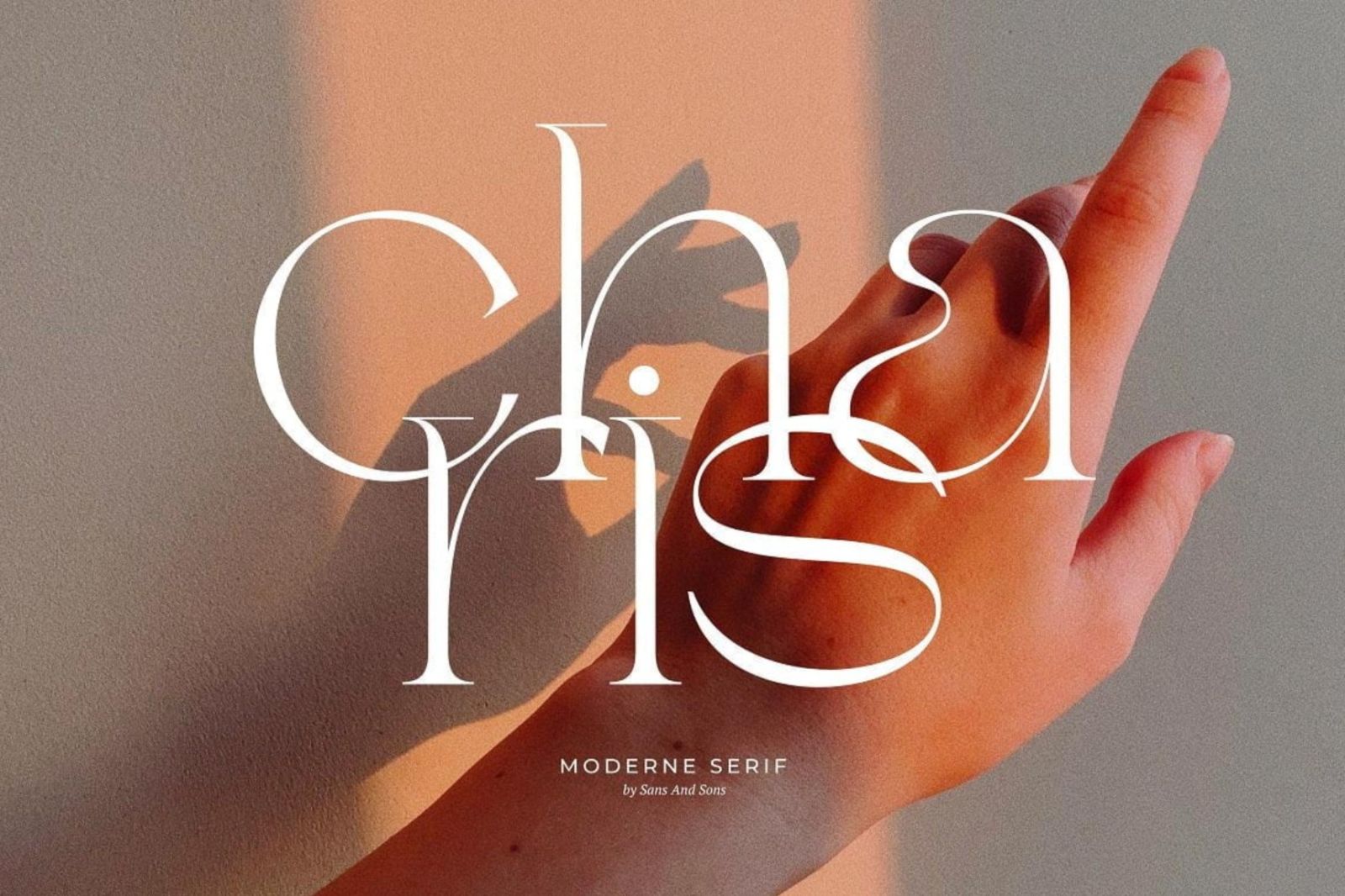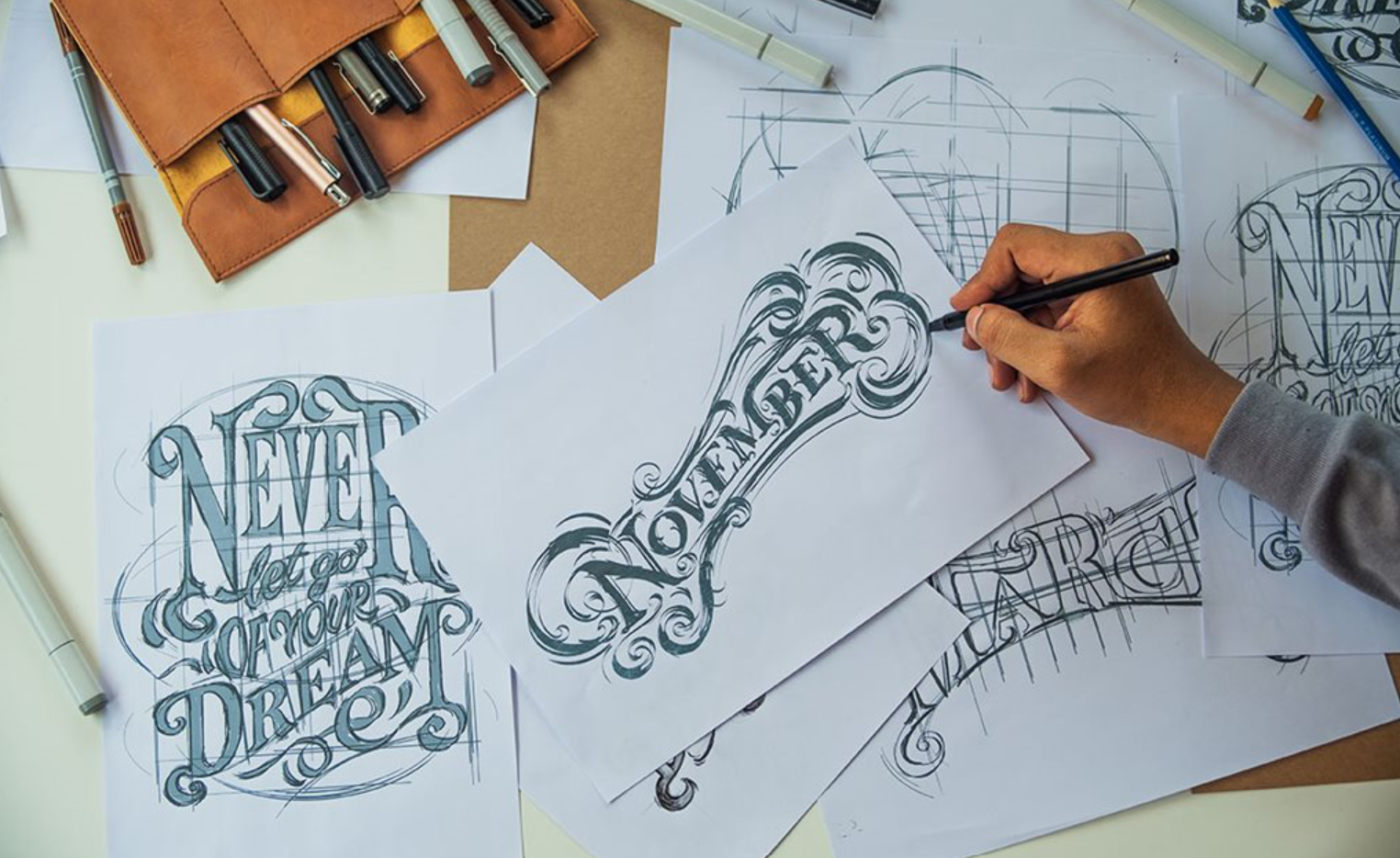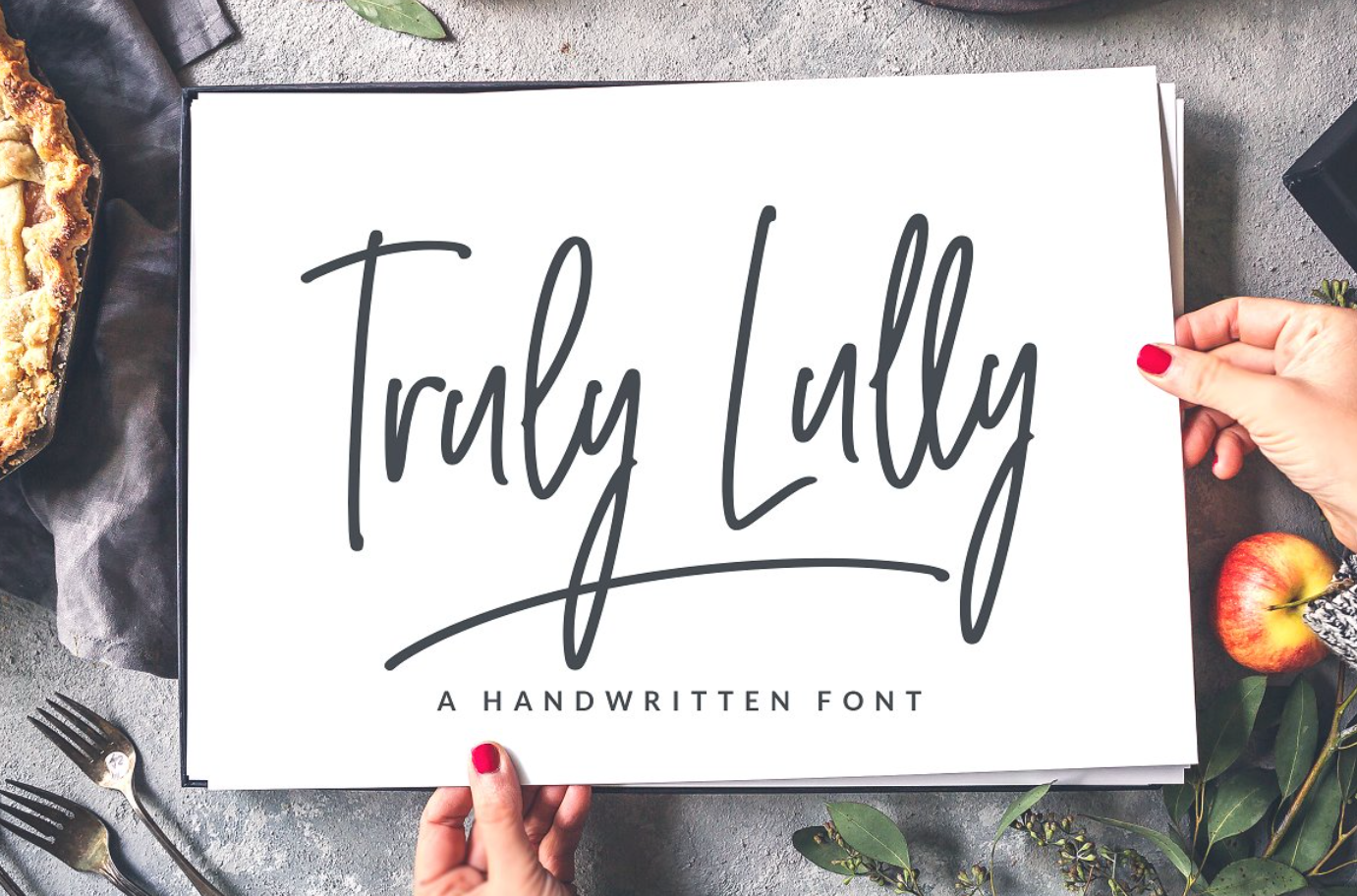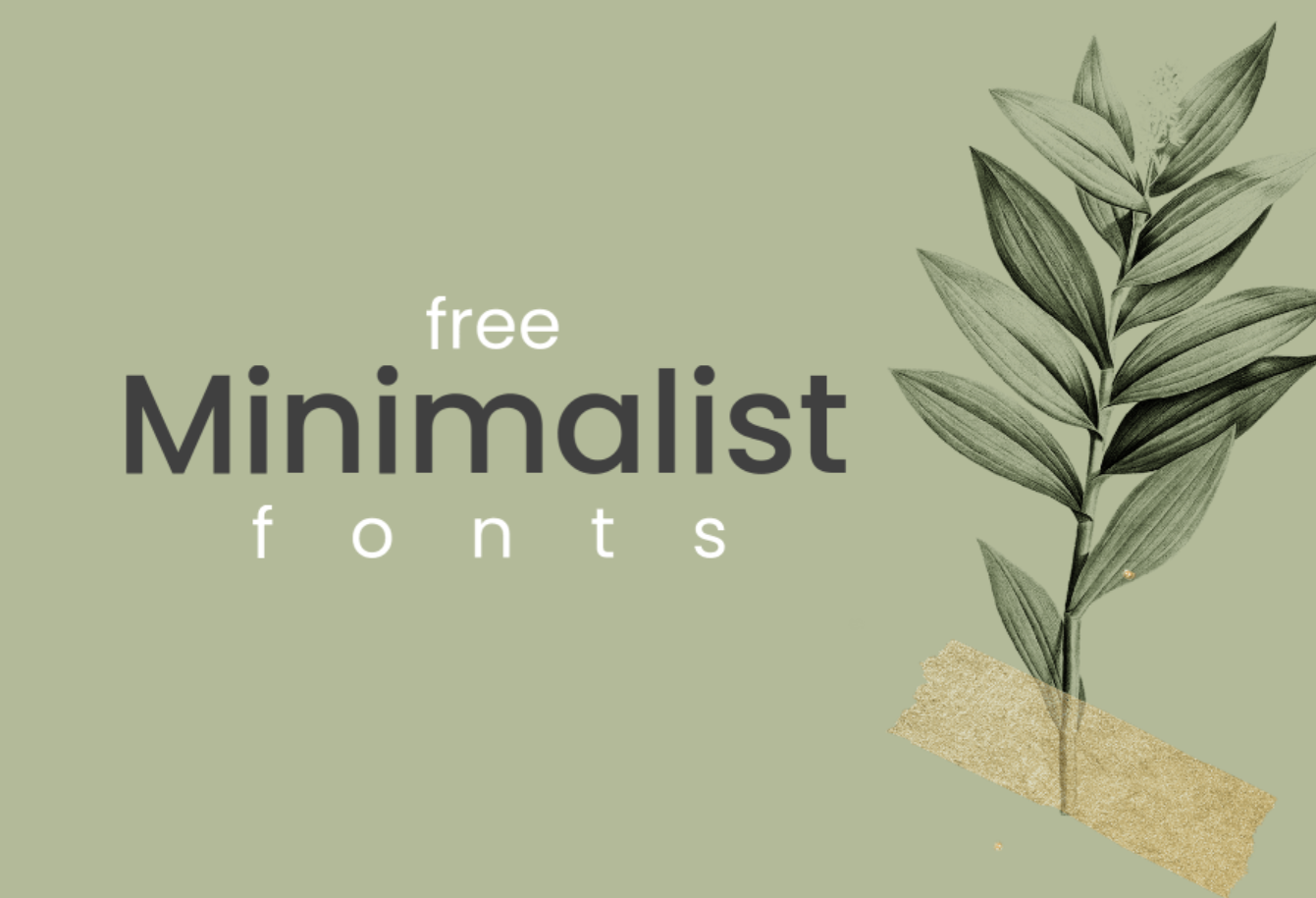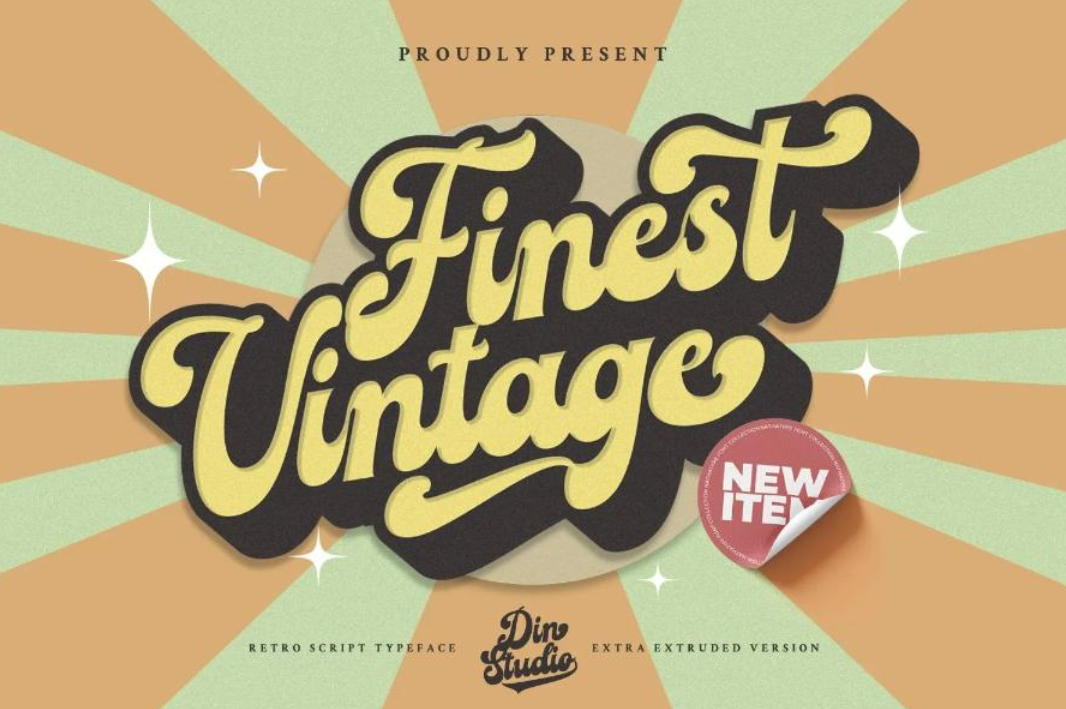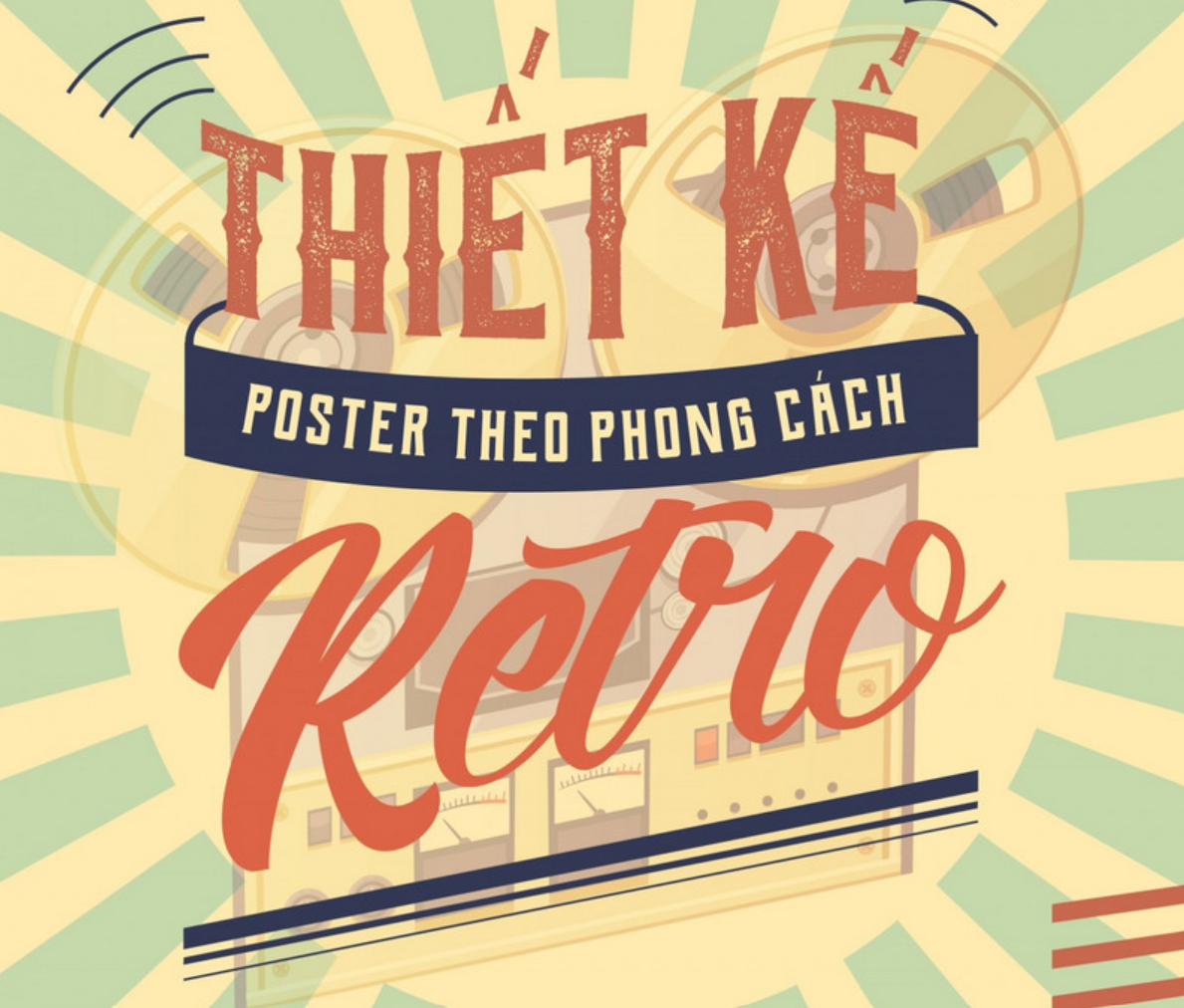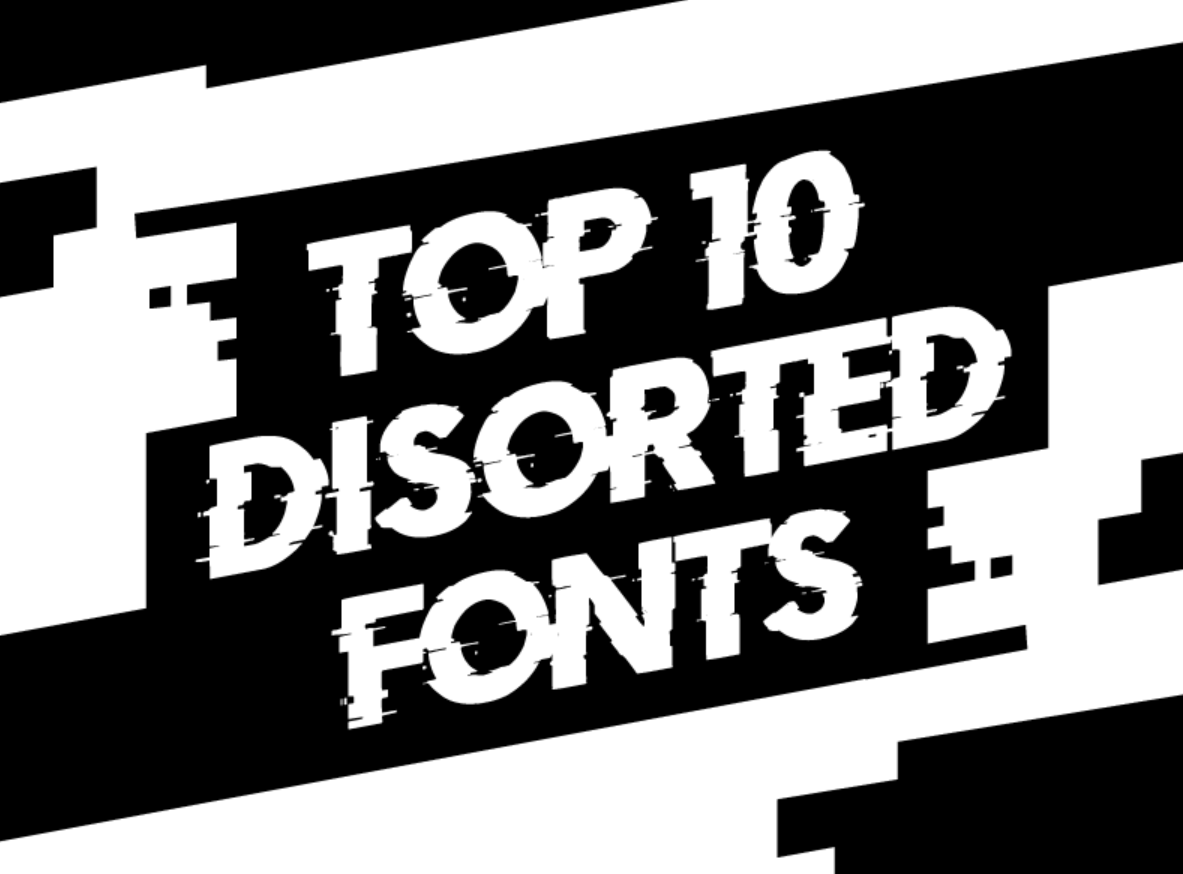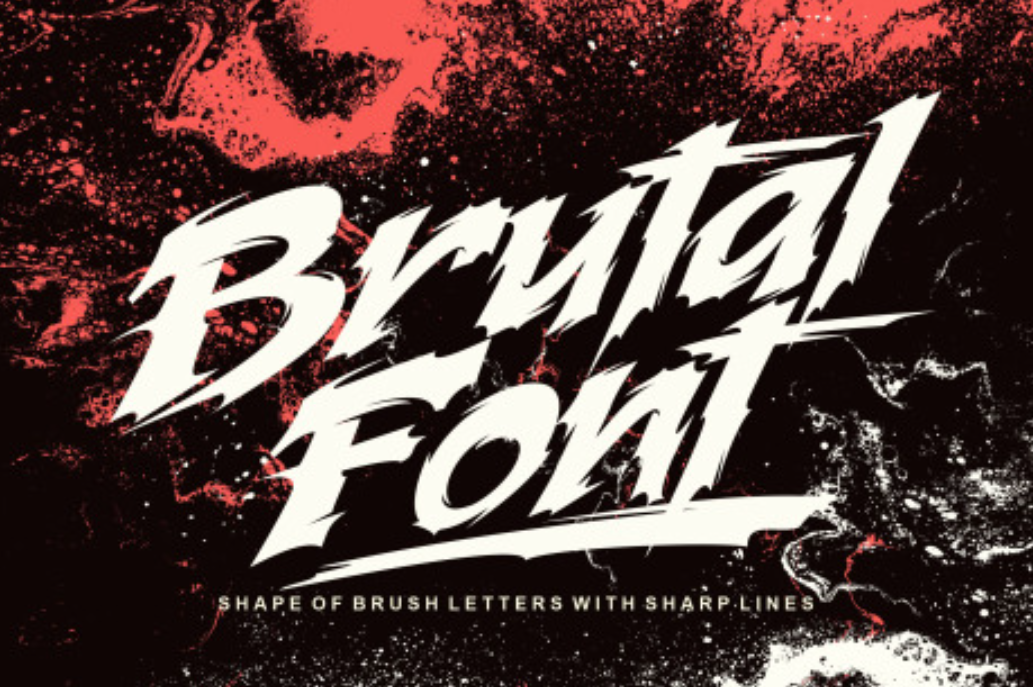
Đột Phá Cùng 6 Xu Hướng Font Chữ Đẹp Tạo Nên Sự Khác Biệt Trong Mỗi Thiết Kế Của Bạn
Bài viết giới thiệu sáu xu hướng typography đột phá, mở ra những hướng đi mới cho thiết kế hiện đại. Bạn sẽ được cập nhật những phong cách chữ sáng tạo cùng với phân tích chi tiết về cách ứng dụng chúng để nâng tầm dự án thiết kế của mình.
Trong thế giới thiết kế, font chữ không chỉ đơn thuần là công cụ để truyền tải thông điệp mà còn là yếu tố quyết định giúp tạo nên phong cách, cá tính và nhận diện thương hiệu. Một thiết kế hoàn hảo luôn biết cách kết hợp màu sắc, hình ảnh và đặc biệt là typography – nghệ thuật sắp xếp chữ để kể câu chuyện của mình một cách sống động nhất. Trong bài viết này, SaDesign sẽ chia sẻ với bạn 6 xu hướng font chữ đẹp đang được dự đoán sẽ “bùng nổ” trong thời gian tới. Hãy cùng khám phá những xu hướng này, tìm hiểu nguồn cảm hứng cũng như cách ứng dụng sao cho hiệu quả nhất trong công việc thiết kế của bạn.
1. Tầm Quan Trọng của Font Chữ Trong Thiết Kế
Trước khi đi sâu vào chi tiết các xu hướng, hãy cùng nhau tìm hiểu tại sao font chữ lại đóng vai trò quan trọng đến vậy trong thiết kế. Mỗi con chữ không chỉ đơn thuần là những ký tự, mà còn ẩn chứa trong đó tâm hồn và cá tính của thương hiệu. Một font chữ được lựa chọn kỹ càng có thể:
Tạo dấu ấn riêng: Font chữ giúp thương hiệu của bạn trở nên dễ nhận diện hơn, tạo nên ấn tượng sâu sắc ngay từ cái nhìn đầu tiên.
Kể câu chuyện thương hiệu: Qua phong cách, nét chữ có thể truyền tải câu chuyện, giá trị cốt lõi và cảm xúc mà thương hiệu muốn gửi gắm.
Tối ưu hóa trải nghiệm người dùng: Trong thiết kế web hay ứng dụng, font chữ không chỉ cần đẹp mà còn phải dễ đọc, tạo cảm giác thoải mái cho người dùng.
Qua đó, việc theo dõi và áp dụng các xu hướng font chữ mới không chỉ giúp bạn bắt kịp thời đại mà còn nâng tầm giá trị thiết kế, tạo nên sự khác biệt nổi bật trên thị trường. Hãy cùng SaDesign đi sâu vào từng xu hướng cụ thể dưới đây.
2. 6 Xu Hướng Font Chữ Húa Hẹn Sẽ Bùng Nổ Trong Thời Gian Tới
2.1: Font Chữ Serif Cổ Điển Nhưng Hiện Đại (Modern Classic Serif)
Font chữ Serif từ lâu đã được biết đến với nét thanh lịch, cổ điển và truyền thống. Tuy nhiên, xu hướng hiện nay không dừng lại ở sự cũ kỹ mà đang hướng đến việc cách điệu, làm mới nét chữ truyền thống để trở nên hiện đại hơn. Xu hướng Modern Classic Serif kết hợp giữa sự sang trọng của những nét cũ và phong cách tối giản, hiện đại của thiết kế ngày nay.
Vì Sao Xu Hướng Này Nổi Bật?
Sự kết hợp độc đáo: Việc pha trộn giữa nét cổ điển và phong cách hiện đại tạo nên một sự hòa quyện độc đáo, giúp chữ viết trở nên nổi bật mà vẫn giữ được nét trang nhã.
Tạo cảm giác tin cậy: Font chữ Serif truyền thống thường gợi lên cảm giác ổn định, uy tín. Khi được cách điệu hiện đại, nó vừa mang lại cảm giác cổ điển vừa hiện đại, rất phù hợp với các thương hiệu cao cấp.
Ứng dụng linh hoạt: Xu hướng này không chỉ phù hợp với thiết kế in ấn, tạp chí mà còn được ứng dụng mạnh mẽ trong thiết kế website, blog hay branding.
Sau khi khám phá xu hướng hiện đại trong nét chữ cổ điển, chúng ta hãy chuyển sang một xu hướng mang đậm dấu ấn cá nhân và nghệ thuật font chữ viết tay. Đây là phong cách đem lại sự ấm áp và tự nhiên, giúp thiết kế của bạn trở nên độc đáo và gần gũi hơn với người dùng.
2.2: Font Chữ Handwritten (Viết Tay, Vẽ Tay Đầy Nghệ Thuật)
Trong thời đại số hóa, nơi mà máy móc và công nghệ luôn thống trị, phong cách Handwritten lại đem đến một làn gió mới – sự tự nhiên, cá tính và gần gũi. Font chữ viết tay không chỉ phản ánh cái tôi riêng của từng nghệ sĩ mà còn tạo nên một không gian “thân mật”, như đang trò chuyện cùng bạn qua từng nét chữ.
Vì Sao Xu Hướng Này Nổi Bật?
Mang đậm chất cá nhân: Font chữ viết tay thể hiện sự độc đáo và cá tính riêng biệt của từng tác giả, từ đó tạo nên dấu ấn riêng cho thương hiệu.
Tạo cảm giác ấm áp, thân thiện: Không khí “viết tay” luôn gợi nhắc đến sự gần gũi, mộc mạc, rất thích hợp cho những thương hiệu muốn xây dựng hình ảnh ấm cúng và thân thiện.
Phù hợp với nhiều ngành nghề: Từ thiết kế thiệp mời, menu nhà hàng cho đến các sản phẩm handmade, font chữ này luôn mang lại sự khác biệt nổi bật.
Với xu hướng mang đậm nét nghệ thuật của chữ viết tay, chúng ta dễ dàng nhận ra sự chuyển biến mạnh mẽ của phong cách thiết kế qua từng thời đại. Tuy nhiên, không phải lúc nào sự phức tạp và tinh tế cũng là ưu điểm. Đôi khi, sự tối giản lại mang đến một sức hút riêng. Hãy cùng chuyển sang xu hướng tiếp theo, font chữ Sans-serif tối giản - nơi sự đơn giản nhưng không kém phần hiện đại lại tạo nên giá trị thẩm mỹ đặc biệt.
2.3: Font Chữ Sans-serif Tối Giản (Minimalist Sans-serif)
Trong bối cảnh thiết kế hiện đại, xu hướng tối giản (minimalism) được ưa chuộng không chỉ bởi vẻ đẹp thanh lịch mà còn bởi khả năng tối ưu hóa trải nghiệm người dùng. Font chữ Sans-serif, loại chữ không có “chân” trở thành biểu tượng của sự hiện đại, sạch sẽ và dễ đọc.
Vì Sao Xu Hướng Này Nổi Bật?
Đơn giản nhưng hiệu quả: Thiết kế tối giản giúp người đọc dễ dàng nắm bắt thông tin mà không bị phân tâm bởi các chi tiết phức tạp.
Tính chuyên nghiệp: Font Sans-serif mang lại cảm giác hiện đại, chuyên nghiệp, phù hợp với các thương hiệu công nghệ, startup hay doanh nghiệp hiện đại.
Đa dạng ứng dụng: Không chỉ được sử dụng trong thiết kế website, ứng dụng di động, mà còn xuất hiện phổ biến trong các ấn phẩm quảng cáo và branding.
2.4: Font Chữ Retro & Vintage (Cổ Điển Nhưng Đầy Cá Tính)
Xu hướng Retro & Vintage là sự kết hợp giữa quá khứ và hiện tại. Trong bối cảnh mà thị trường tràn ngập những thiết kế hiện đại tối giản, những nét chữ mang hơi thở của thời gian đã qua lại mang lại một sự tươi mới và độc đáo, như thể chúng ta vừa lạc vào một kho tàng ký ức của thập niên 70, 80. Phong cách này không chỉ gợi nhớ đến một thời kỳ đặc biệt mà còn mang lại sự sáng tạo, phá cách và cá tính riêng.
Vì Sao Xu Hướng Này Nổi Bật?
Sự hoài cổ đầy mê hoặc: Những nét chữ mang đậm chất Retro & Vintage thường gợi lên cảm giác nhớ về những kỷ niệm xưa cũ, làm cho người xem cảm thấy gần gũi và thân thuộc.
Sự kết hợp giữa quá khứ và hiện đại: Khi được cách điệu, những font chữ cổ điển này lại trở nên “năng động” và hiện đại hơn, tạo nên một hiệu ứng thị giác độc đáo.
Thể hiện cá tính riêng: Phong cách retro không chỉ là sự hoài niệm mà còn thể hiện sự phá cách, cá tính, rất phù hợp cho các thương hiệu muốn tạo dấu ấn khác biệt.
Chúng ta vừa dạo qua quá khứ với những nét chữ đầy hoài cổ của phong cách Retro & Vintage. Giữa lúc thị trường đang dần hướng về sự tân tiến và phá cách, không thể không nhắc đến xu hướng mang tính “đột phá” đó là font chữ biến dạng. Xu hướng này hứa hẹn sẽ tạo nên những “cú hích” mạnh mẽ cho các thiết kế hiện đại và sáng tạo.
2.5: Font Chữ Biến Dạng (Variable & Distorted Fonts)
Xu hướng Font chữ biến dạng đang dần khẳng định vị thế của mình trong làng thiết kế với những nét chữ “bất đối xứng”, bị bóp méo, kéo giãn hoặc biến đổi theo hiệu ứng động. Đây là phong cách phá vỡ khuôn mẫu truyền thống, mang lại sức sống mới cho từng thiết kế. Nó không chỉ thể hiện sự sáng tạo, khác biệt mà còn thể hiện tinh thần thử nghiệm, phá cách của các nhà thiết kế hiện đại.
Vì Sao Xu Hướng Này Nổi Bật?
Phá vỡ quy tắc truyền thống: Font chữ biến dạng cho phép designer thoải mái thể hiện tính sáng tạo vượt trội, từ đó tạo nên những thiết kế khác biệt và thu hút sự chú ý.
Tính ứng dụng cao: Dù không phải lúc nào cũng phù hợp với mọi dự án, nhưng khi áp dụng đúng cách, xu hướng này sẽ giúp sản phẩm của bạn trở nên nổi bật trong một thị trường đầy cạnh tranh.
Mang lại cảm giác “năng động” và hiện đại: Các hiệu ứng động, biến đổi của font chữ giúp tạo nên cảm giác chuyển động, sống động cho từng tác phẩm.
Sau khi cùng nhau tìm hiểu về sự phá cách và độc đáo của font chữ biến dạng, chúng ta sẽ tiến tới xu hướng cuối cùng nhưng không kém phần nổi bật – đó là sự kết hợp giữa hiệu ứng 3D và gradient. Xu hướng này chính là “vũ khí bí mật” giúp cho các thiết kế trở nên nổi bật, sống động và đầy mê hoặc.
2.6: Font Chữ 3D & Gradient (Hiệu Ứng Nổi Bật, Sáng Tạo)
Trong thời đại mà công nghệ số phát triển vượt bậc, việc áp dụng các hiệu ứng thị giác như 3D và gradient không chỉ là xu hướng mà còn là nhu cầu tất yếu để tạo nên sự hấp dẫn cho thiết kế. Font chữ 3D & Gradient kết hợp giữa chiều sâu, hiệu ứng ánh sáng và màu sắc chuyển đổi mượt mà, mang lại một diện mạo mới lạ cho từng ký tự.
Vì Sao Xu Hướng Này Nổi Bật?
Tạo hiệu ứng nổi bật: Các hiệu ứng 3D và gradient không chỉ làm cho chữ viết trở nên sống động mà còn tạo ra ấn tượng mạnh mẽ ngay từ cái nhìn đầu tiên.
Mang lại cảm giác hiện đại và công nghệ: Phong cách này rất phù hợp với các thương hiệu trong lĩnh vực kỹ thuật số, game, và công nghệ, nơi mà sự hiện đại và sáng tạo luôn được đề cao.
Đa dạng về ứng dụng: Từ thiết kế poster quảng cáo, giao diện web đến các ấn phẩm truyền thông, font chữ 3D & Gradient đều có thể tạo ra những điểm nhấn thị giác đầy ấn tượng.
3. Lời Khuyên Cho Các Nhà Thiết Kế
Lựa chọn font chữ phù hợp với thông điệp thương hiệu: Mỗi thương hiệu đều có câu chuyện riêng, hãy chọn những nét chữ có khả năng truyền tải đúng thông điệp mà bạn muốn gửi gắm.
Đừng ngại thử nghiệm: Dù là xu hướng cổ điển hay hiện đại, đừng ngại thử nghiệm sự kết hợp giữa các phong cách khác nhau để tạo ra một sản phẩm độc đáo.
Tính linh hoạt trong thiết kế: Hãy luôn nhớ rằng font chữ không chỉ để “đọc” mà còn để tạo nên cảm xúc. Sự linh hoạt trong việc kết hợp font chữ với màu sắc, hình ảnh và bố cục sẽ giúp bạn tạo ra những thiết kế nổi bật.
Cập nhật xu hướng: Thế giới thiết kế luôn biến đổi. Việc theo dõi và cập nhật những xu hướng mới sẽ giúp bạn luôn đi trước thời đại, tạo nên sự khác biệt cạnh tranh.
Từ những nét chữ cổ điển đến những hiệu ứng hiện đại, mỗi xu hướng đều mở ra một cánh cửa mới cho những nhà thiết kế khám phá và sáng tạo. Không có một công thức cố định nào cho sự thành công, nhưng điều chắc chắn là, khi bạn hiểu và áp dụng đúng xu hướng font chữ, sản phẩm của bạn sẽ không chỉ là một tác phẩm nghệ thuật mà còn là công cụ truyền tải thông điệp mạnh mẽ và hiệu quả.